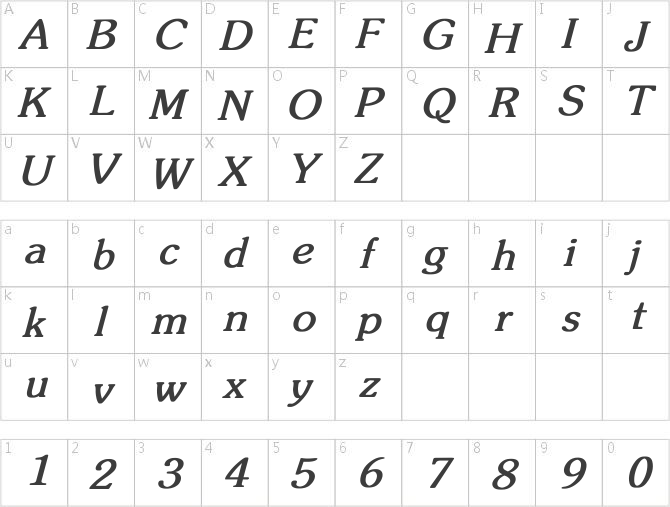
Flickner-Bold-Italic 詳情頁
Flickner-Bold-Italic字體字庫是一款讓人賞心悅目、百看不厭的英文字體,適合各類廣告和產(chǎn)品包裝設(shè)計(jì)應(yīng)用,字體大小0.1MB,格式為ttf字體,上傳用戶是一直在守護(hù),作者/版權(quán)方為未知